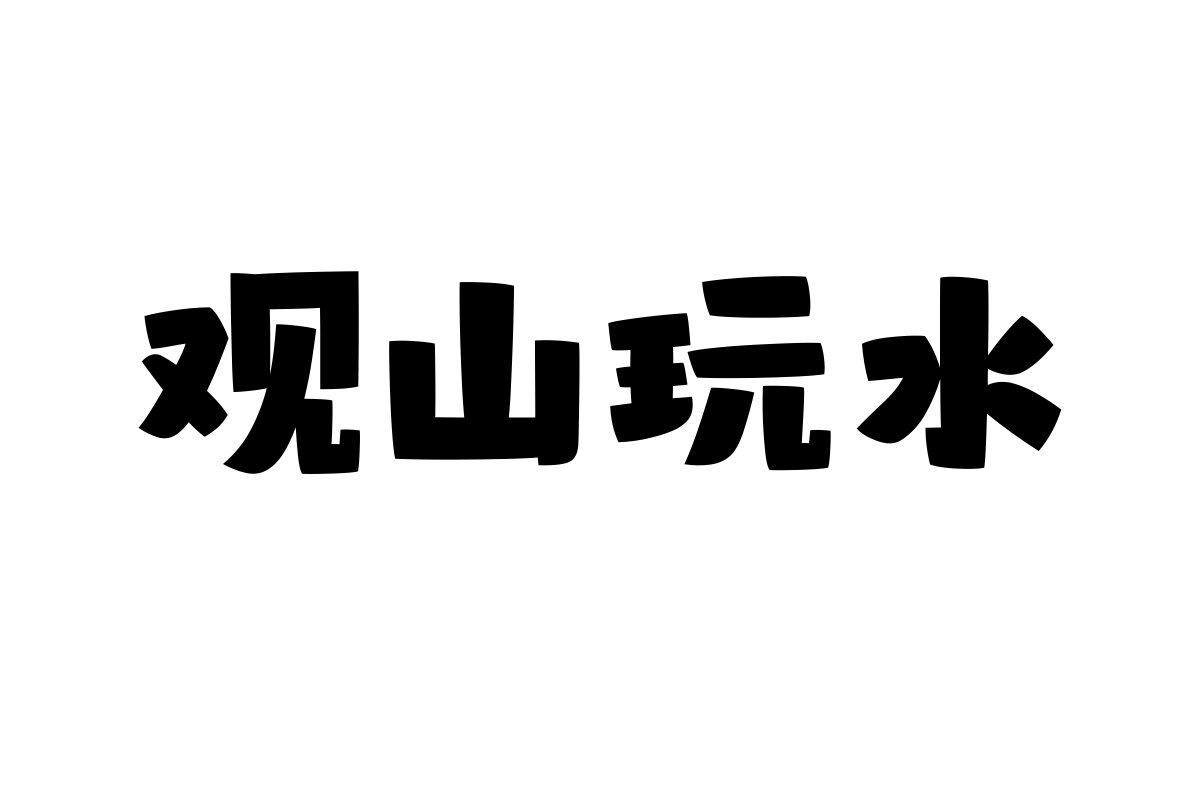
山海小怪兽字体是一款现代感十足的中文手写体,具有独特的艺术风格和流畅的书写效果。这款字体由设计师精心打造,融合了传统的书法元素和现代的设计手法,使其既有古典韵味又不失现代时尚感。
山海小怪兽字体的特点包括:
1. 字形独特:每个字都采用了独特的造型设计,线条流畅自然,富有动感。
2. 风格多样:无论是用于标题、正文还是装饰性文字,都能展现出不同的风格和氛围。
3. 易于识别:字体结构清晰明了,笔画粗细适中,便于阅读和识别。
4. 适用广泛:适用于各种场合,如书籍、杂志、海报、广告等,具有较高的实用性和观赏价值。
总之,山海小怪兽字体是一款集美观与实用于一体的中文手写体,适合各类文本创作和设计需求。